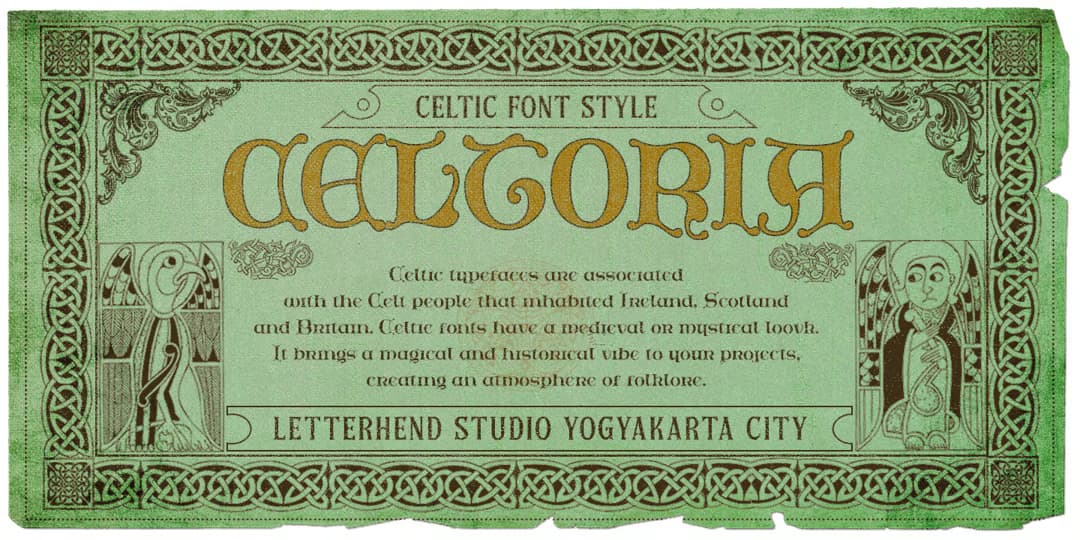
Celtoria
ケルト風味あふれるディスプレイ。中世アイルランドやイングランドで用いられていたいわゆるインシュラー Insular をベースにした書体で、元々は大文字小文字の区別がないが、こちらはインシュラーのテイストを保ちつつ、大文字小文字がデザインされている。なんとなくロンバルディックキャピタルに見えなくもないが(笑)、まあそこら辺は良しとしよう。ハロウィンは元々ケルト人の祭りで、こんなのもよく似合うので紹介してみた。